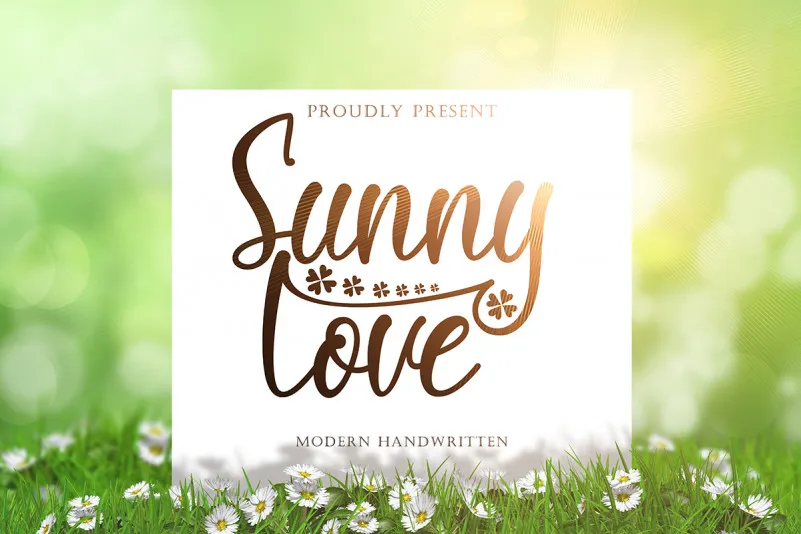
Esta é uma linda fonte escrita a mão. Foi projetada para trazer uma sensação de leveza e beleza à sua identidade visual. As letras são decoradas com ricos detalhes que adicionam um toque único, tornando cada letra ainda mais especial. Este conjunto perfeito para o seu dia a dia, seja durante as férias, nos meses de verão ou primavera, em ocasiões familiares como Dia das Mães e Dia dos Pais, ou até mesmo no design gráfico para logos, marcas branding, panfletos, convites, presentes, aniversários, casamentos, mídias sociais, cartas e mensagens personalizadas. A instrução de uso é bastante simples, fazendo com que seja fácil integrar essa fonte em seu trabalho diário ou projetos gráficos mais elaborados. Sem dúvidas, Sunny Love Font é uma escolha perfeita para quem busca um toque delicado e autêntico nas suas criações.